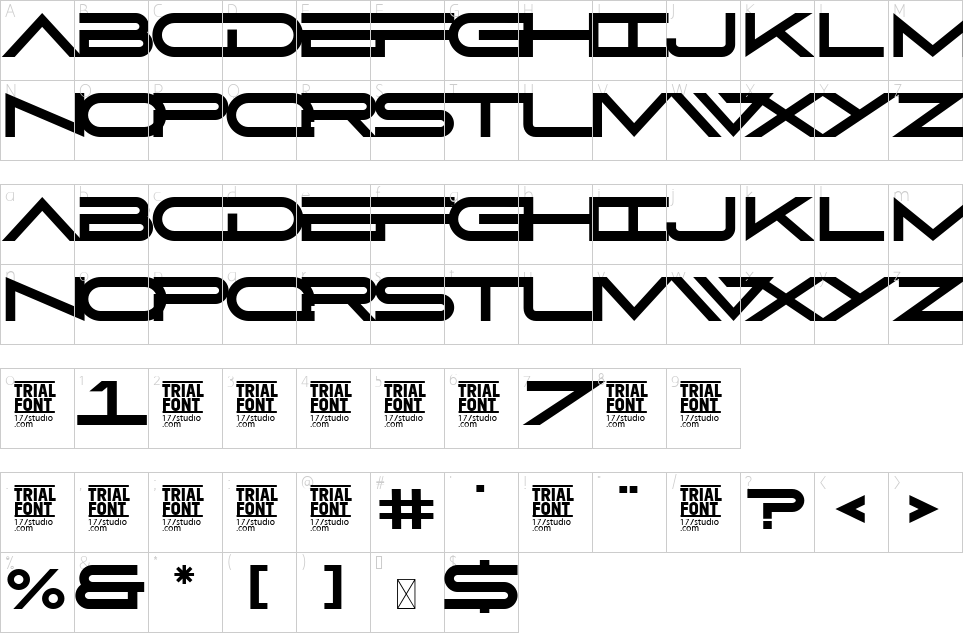
Esta fonte Digital Cards oferece uma abordagem moderna para criar cartões digitais, perfis de redes sociais ou qualquer outro tipo de material digital que exija uma aparência elegante e profissional. Desenvolvida por 177studio.com, esta font é ideal para quem procura um equilíbrio perfeito entre simplicidade e estética moderna. Suportando tanto Windows quanto Mac, a Digital Cards permite que você personalize seus designs de maneira eficiente sem comprometer a qualidade visual. Com design minimalista, ela se adapta facilmente a diversas tamanhos de texto e formatos para criar uma variedade imensa de propósitos gráficos. O fato de ser gratuita não significa diminuir o valor desta fonte; ao contrário, seu baixo custo permite que você utilize-a sem restrições em projetos pessoais ou comerciais. Em um mundo cada vez mais digitalizado, uma boa fonte pode fazer toda a diferença no sucesso visual do seu conteúdo. Com o Digital Cards Font, transforme suas ideias digitais em realidade com uma aparência clara e elegante.